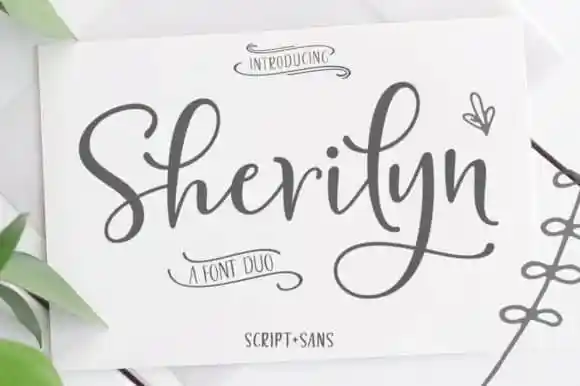
Sherilyn Script Font – Download Grátis
Estamos encantados de apresentar a Sherilyn Script Font, uma nova opção para designers que buscam uma tipografia moderna e sofisticada. Este é um script calligráfico que traz uma visão única dos elementos do tipo moderno, com uma aparência elegante e romântica. Perfeito tanto para projetos profissionais como para trabalhos mais pessoais, como revistas casamentares, capas de livros, cartões de agradecimento, logotipos, identidades corporativas, cartões de visitas ou até mesmo certificados. A Sherilyn Script traz uma combinação leve e romântica com um toque divertido que vai deixar seus projetos ainda mais interessantes. Ela é ideal para quem procura uma fonte clássica que mantém elementos modernos, tornando-a adequada a diversas utilizações que exigem um visual formal e luxuoso. A Sherilyn Script pode se tornar seu novo aliado em qualquer projeto gráfico que exija elegância e sofisticação. Não deixe de experimentar essa fonte para trazer novas ideias para seus trabalhos!